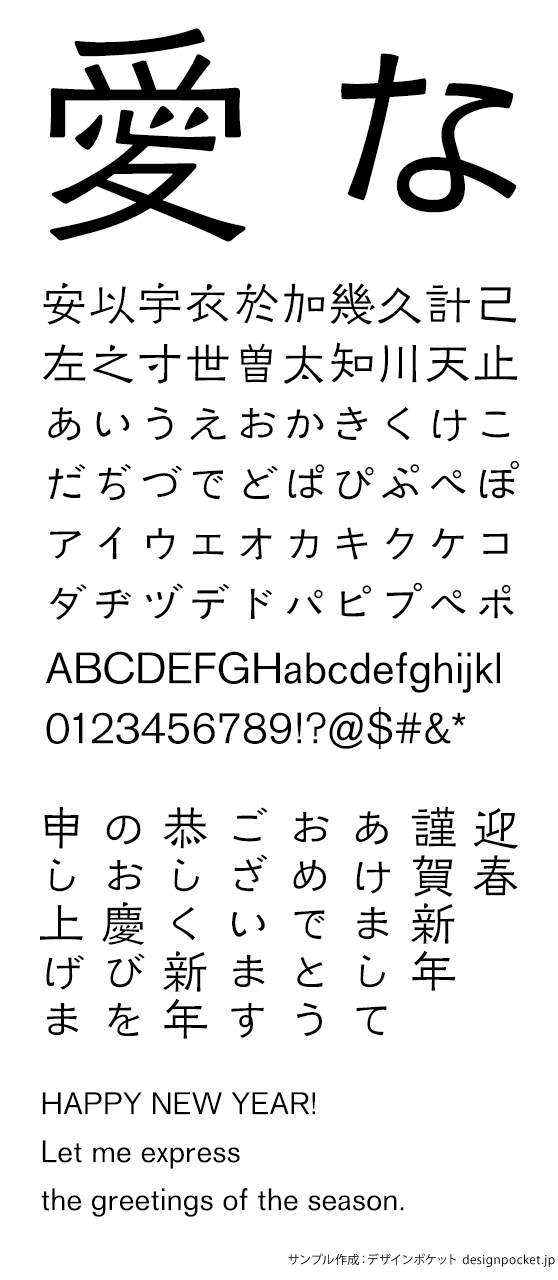
角ゴシック
KOくらもち銘石M
KOKuramochiMeiseki-M
『活版見本』(東京築地活版製造所、1903)掲載の「五号二分ノ一ゴチックひらがな」を復刻した「くらもち」に、『王興之墓誌』(341)と『王興之妻宋和之墓誌』(348)にもちいられた字様をもとに翻刻した「銘石」、1898年にドイツ・ベルリンのベルトルド活字鋳造所が製作した「アクチデンツ・グロテスク」をベースにした「K.E.Sagittarius」を組み合わせた「KOくらもち銘石B」のファミリーで、メディウム・ウエイトです。
KOくらもち銘石M